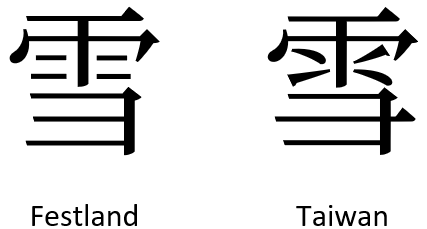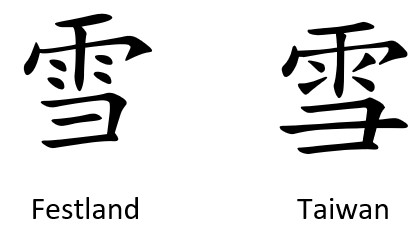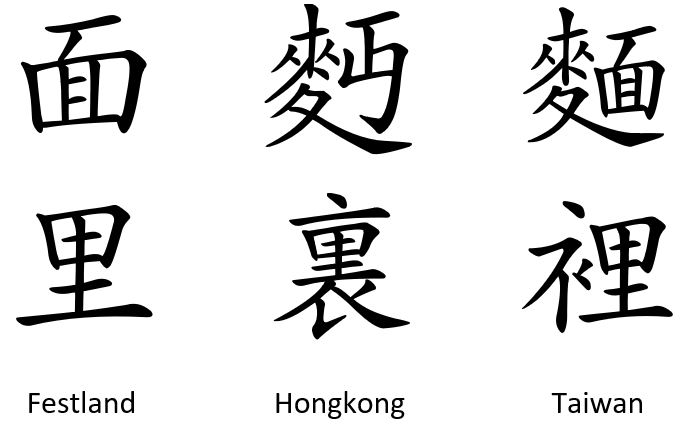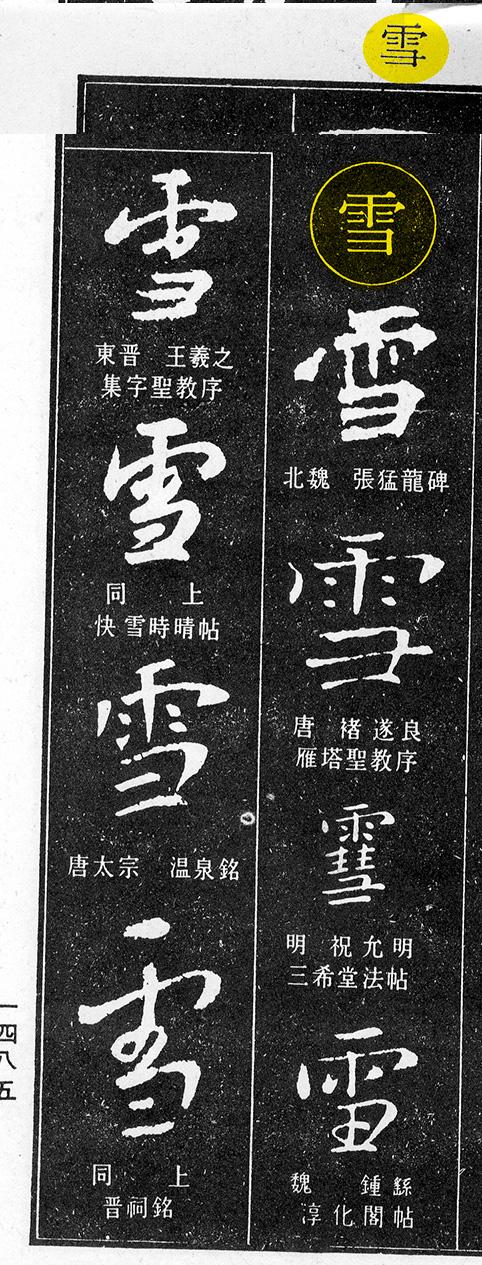
Asiatische Entsprechung zur FF Din
ich suche Schriftexperten für Chinesisch und Japanisch. Das Thema ist mit Sicherheit trocken uns außerordentlich komplex, aber vielleicht kennt sich ja jemand damit aus. Mein Kunde verwendet die FF DIN und nun gilt es für China und Japan eine Entsprechung zu finden.
Welche Zeichenform für China: Traditionell oder vereinfacht? Und warum?
Beinhaltet ein Font, der als Chinesisch ausgewiesen ist, beide Zeichenformen?
Welche Zeichenform für Japan: Hiragana, Katakana und Kanji oder alle 3? Und warum?
Beinhaltet ein Font, der als Japanisch ausgewiesen ist, alle 3 Zeichenformen?
Kann eine Schrift sowohl die Zeichensätze von Chinesisch, als auch Japanisch beinhalten? Das wäre enorm praktisch!
Wenn ich diese Grundvorraussetzungen geklärt habe, beginnt die Suche nach einem Font, der zur FF-Din passt. Natürlich freue ich mich auch hier über gute Empfehlungen.
Wir haben ebenfalls einen internationalen Kunden, der die DIN verwendet. Dieser hat sich für die "Arial Unicode MS" entschieden, die Chinesisch und Japanisch beinhaltet und von den Formen her so schnörkellos daherkommt wie die DIN.
Welche Zeichenform für China: Traditionell oder vereinfacht? Und warum?
Beinhaltet ein Font, der als Chinesisch ausgewiesen ist, beide Zeichenformen?
Vereinfacht für die Voksrepublik China, traditionell für Taiwan, Hongkong und Singapur. Aus meiner persönlichen Erfahrung rate ich zu zwei verschiedenen Fontvarianten (TC/SC), so kann z.B. von Lang- auf Kurzzeichen (und zurück) umgestellt werden, ohne über die "Dienste" (beim Mac) konvertieren zu müssen. Wenn's blöd läuft, kann nämlich unter Umständen nicht korrekt zurückkonvertiert werden, da es (wenige) Kurzzeichen gibt, denen mehrere Langzeichen zugeordnet werden können.
Welche Zeichenform für Japan: Hiragana, Katakana und Kanji oder alle 3? Und warum?
Beinhaltet ein Font, der als Japanisch ausgewiesen ist, alle 3 Zeichenformen?
"Japanisch" beinhaltet alle drei. Denn Kanji und Kana (Hiragana, Katakana) erfüllen unterschiedliche Funktionen. Zu beachten ist, dass manche Kanji und chinesische Zeichen (obwohl eigentlich das gleiche Zeichen) unterschiedliche Zeichenformen besitzen. Man sollte also nicht versuchen, Kanji durch "Chinesisch" zu ersetzen.
Wichtig ist auch die Frage nach der Anzahl der Glyphen. Sollte es doch "ein Font für alles" sein, müsste er mindestens 30.000, besser noch ca. 50.000 Glyphen enthalten. Den DIN-Formen entsprechen die von bertel genannte Arial, die von Moritzk verlinkte Noto Sans CJK sowie auch andere als "Hei" bezeichnete Fonts.
Wir haben die Noto Sans CJK (JP/SC/TC/KR) intensiv im Einsatz gepaart mit der DIN Pro.
• formal nicht ganz weit weg (wenn auch nicht wirklich "DIN")
• 7 verfügbare Schriftgewichte, entsprechen annähernd denen der DIN Pro
• moderne Fontdaten mit Unicode-Codierung, Opentype-Features und Postscript-Kurven, moderne Überlegungen bei der Konzeptionierung
• getrennte Pakete für Koreanisch, Simplified-Chinese, Traditional-Chinese und japanisch (soweit ich das sehe, kann man auch die anderen Sprachen mit jedem der 4 Pakete setzen, aber wer bin ich das im letzten Detail beurteilen zu können ... sicher ist sicher ...)
• für den Fall der Fälle auch Fonts für Indien, den arabischen Raum etc. etc. verfügbar, also dann nicht nochmal eine andere Schrift im Spiel
• Webfonts verfügbar, also dann nicht nochmal eine andere Schrift im Spiel
... das sind viele praktische und wenige grafische Gründe, aber aus Erfahrung weiß ich, dass man da auch einen schönen Tod sterben kann wenn man mit einem technischen Dinosaurier agiert, der dafür der lateinischen Schrift 10% ähnlicher ist ... lieber nicht mehr.
vor 10 Stunden schrieb Sebastian Nagel:
der lateinischen Schrift 10% ähnlicher ist
... zumal es das für die DIN ohnehin nicht gibt. Die CJK-Sans-Schriften ähneln sich alle sehr, denn es gibt eigentlich nur den einen Hei-Stil, der sich von Schrift zu Schrift nur minimal unterscheidet.  Ein weiteres Plus der Noto: Die vielen Gewichte von Thin bis Black.
Generell gibt es neben der Sans (Hei) noch die Stile Ming bzw. Song (Serif) und Kai (Pinselduktus).
Wer es so richtig besonders haben möchte, guckt mal bei Founder (GB-Standard) oder Hanyi (Lang- und Kurzzeichensätze) – aber da weiß ich nicht, wie groß der Zeichenumfang der Fonts im Einzelfall eigentlich ist.
Man kann nicht denselben Zeichensatz für vereinfachte und traditionelle Schriftzeichen verwenden, selbst wenn der Zeichensatz sowohl vereinfachte als auch traditionelle Zeichen enthält, denn es gibt auch für Zeichen, die »theoretisch« in beiden Systemen identisch sind, zum Teil unterschiedliche Konventionen. Hier ein Beispiel (das Zeichen xuě 雪 »Schnee«):
Die Schriftgestalter bei Adobe und Google wissen schon, was sie tun.
Das heißt nicht, dass man in Aufschriften, Werbematerial und nicht zuletzt eben Kalligrafien etc. manchmal regional »unpassende« Varianten sieht, doch die werden dann als besonderes kalligrafisches Stilmittel eingesetzt. Bei Brotschriften hat man diese Freiheit nicht.